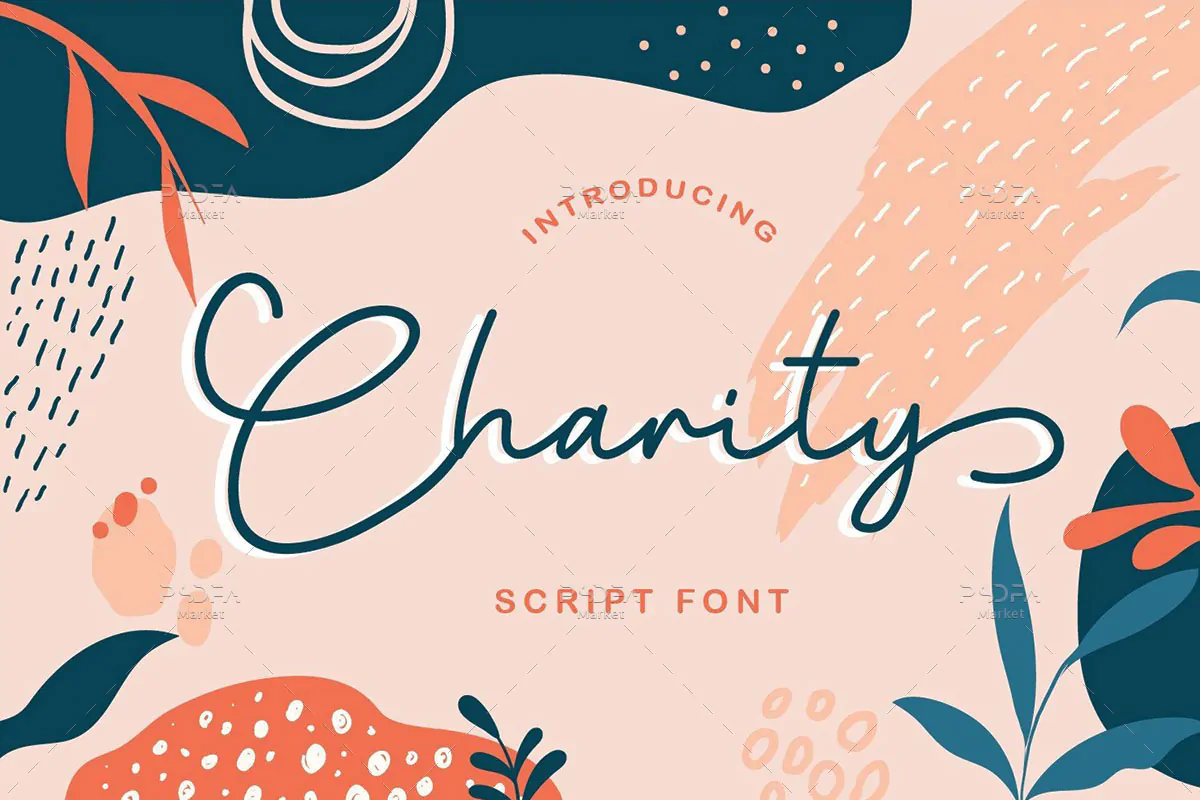
فونت سرهم نویسی Charity
فونت سرهم نویسی
فونت سرهم نویسی Charity یک اسکریپت فونت دستنویس انگلیسی است که مناسب جهت استفاده در طرح و پروژههای گرافیکی مختلف میباشد. فونت Charity با وزن معمولی طراحی شده است که میتوانید از آن در طراحی انواع کارت ویزیت، پوستر، تراکت، بروشور، بسته بندی محصولات، آرایشی و بهداشتی و … استفاده کنید.